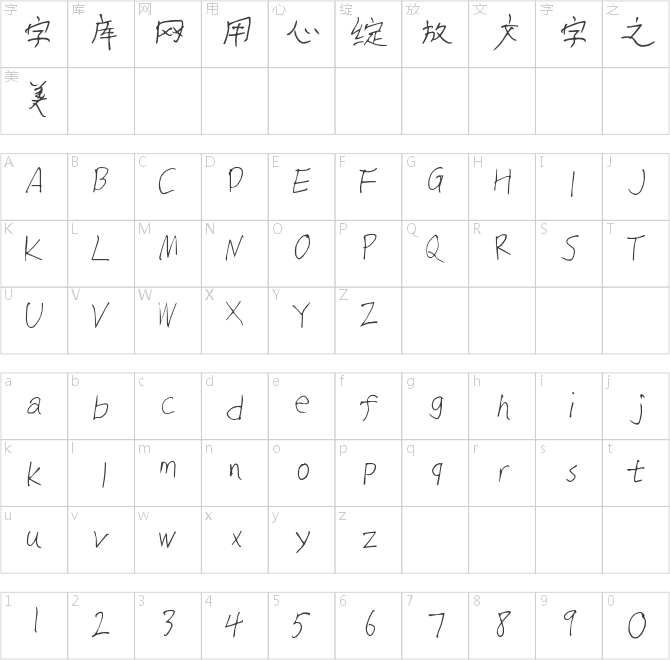
漢卿字體全異體和簡體 詳情頁
字體名稱: 漢卿字體全異體
作者版權: 敬漢卿
B站知名up主敬漢卿手寫字體,由FlexiFont生成
漢卿字體全異體和簡體字體字庫是一款讓人賞心悅目、百看不厭的中文字體,適合各類廣告和產(chǎn)品包裝設計應用,字體大小8.52MB,格式為ttf字體,上傳用戶是小猴子1003,作者/版權方為敬漢卿